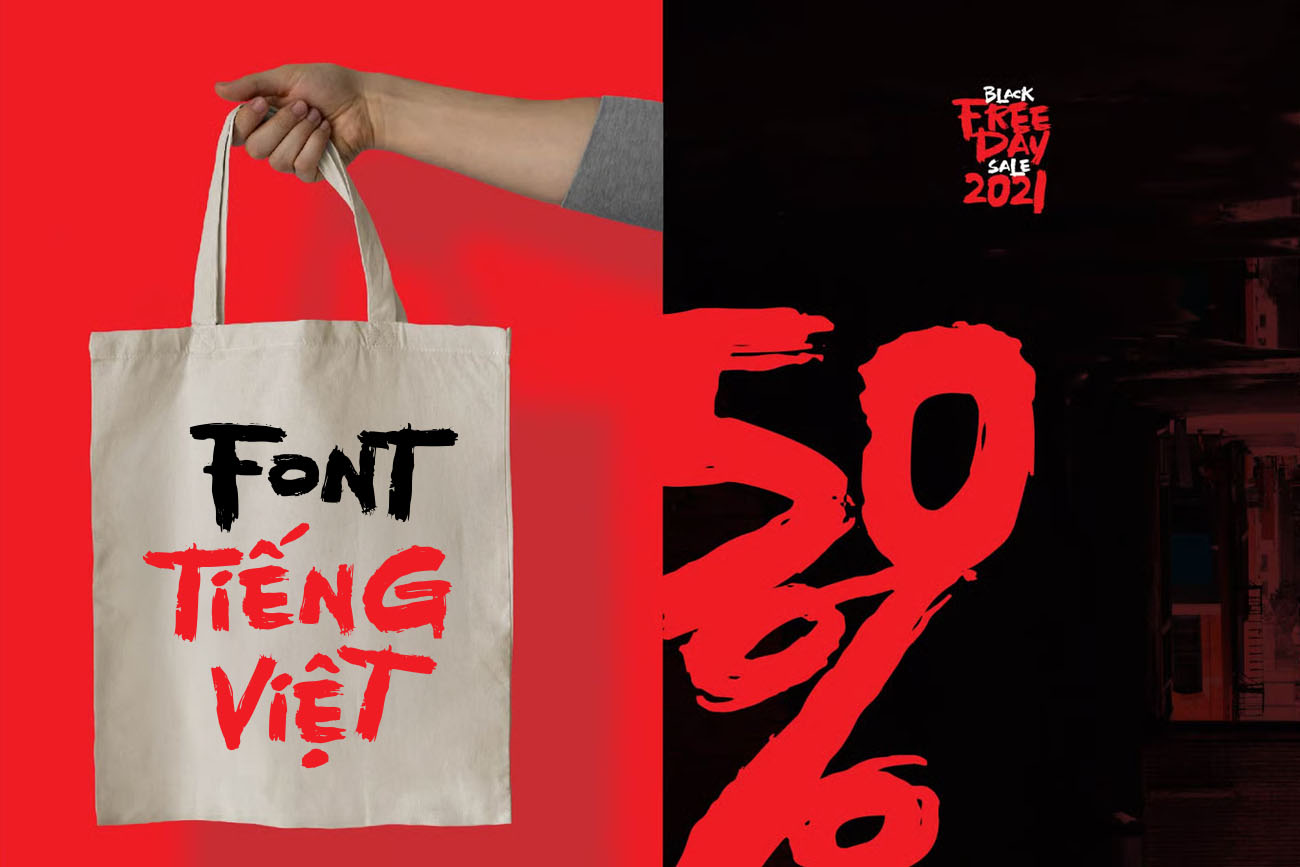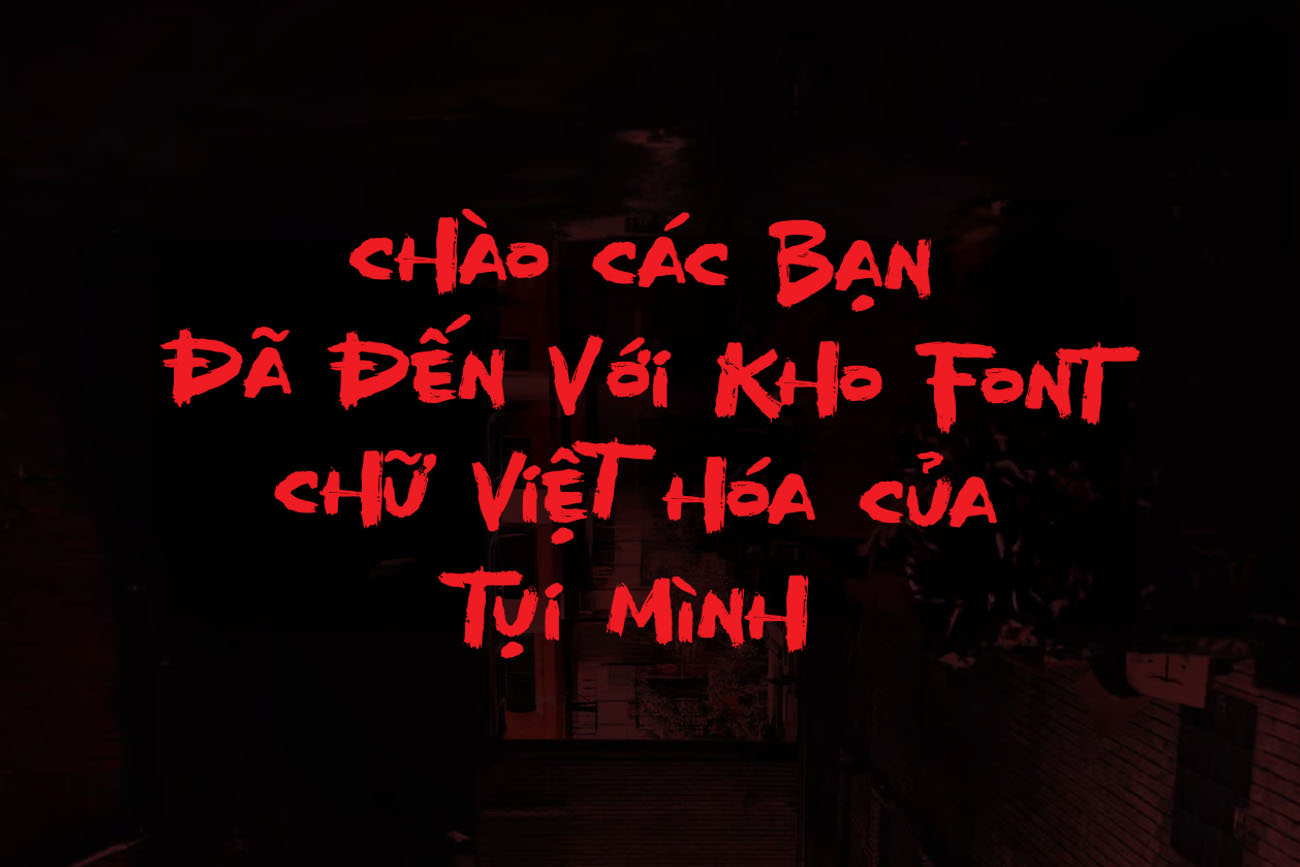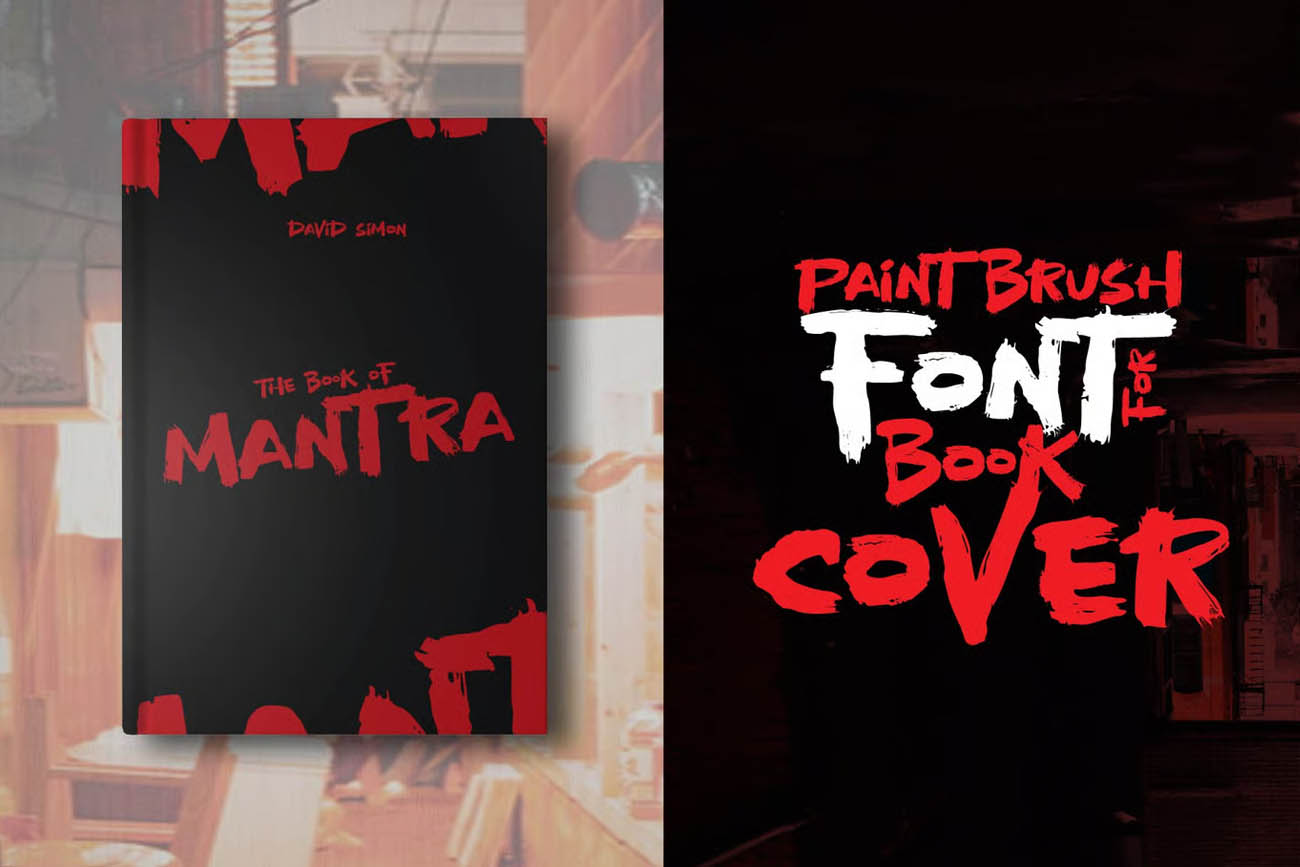
TH Dark Sincity - Sự Phá Cách Hoàn Hảo Cho Các Thiết Kế Mang Đậm Cá Tính
Tác giả Olex Studio
Trong thế giới thiết kế đồ họa, việc tìm kiếm một kiểu chữ thể hiện được sự mạnh mẽ, bụi bặm và gai góc luôn là một yếu tố quan trọng để tạo nên sự khác biệt. Bắt nguồn từ thiết kế gốc [Dark Sincity](https://elements.envato.com/fr/darksincity-display-font-PR9AQZN) của tác giả Olex Studio, phiên bản TH Dark Sincity đã chính thức ra mắt cộng đồng designer Việt. Đây là một luồng gió mới dành riêng cho những ai đang tìm kiếm sự phá cách độc đáo trong từng đường nét typography.
TH Dark Sincity: Sự Phá Cách Hoàn Hảo Cho Các Thiết Kế Mang Đậm Cá Tính
Đặc điểm nổi bật của TH Dark Sincity
Mang đậm hơi thở của văn hóa đường phố, thiết kế này là một font chữ hiphop tiêu biểu với các nét chữ dày dặn, sắc sảo và cấu trúc bất đối xứng đầy nghệ thuật. Không dừng lại ở đó, nhờ vào sự bí ẩn và những đường cắt xước góc cạnh trong từng ký tự, TH Dark Sincity còn được ứng dụng xuất sắc như một font chữ kinh dị trong các poster phim ảnh, bìa sách Halloween hay các ấn phẩm mang phong cách dark aesthetic. Sự đa năng này giúp các nhà thiết kế dễ dàng truyền tải những thông điệp thị giác tột độ và đầy ám ảnh.
Tại sao designer nên chọn phiên bản Việt hóa này?
Trước đây, việc sử dụng các phông chữ nước ngoài có thiết kế đặc thù thường gây khó khăn cho designer Việt vì lỗi hiển thị dấu. Tuy nhiên, với TH Dark Sincity, đây là một font chữ Việt hóa hoàn chỉnh. Các dấu câu được tinh chỉnh tỉ mỉ, đảm bảo tỷ lệ hài hòa tuyệt đối với bộ chữ gốc của Olex Studio. Điều này giúp bạn tiết kiệm tối đa thời gian kerning (chỉnh khoảng cách chữ) và vẽ lại dấu, mang đến trải nghiệm thiết kế mượt mà, chuyên nghiệp.
Đôi nét về đơn vị thực hiện TH Team
Quá trình chuyển ngữ và tối ưu hóa phông chữ này được thực hiện bởi TH Team – một đơn vị chuyên mang đến những giải pháp typography chất lượng cao cho người Việt. Bằng sự am hiểu sâu sắc về cấu trúc chữ cái, TH Team đã giữ nguyên được tinh thần nguyên bản của Dark Sincity trong khi vẫn đáp ứng hoàn hảo các quy tắc đánh vần phức tạp của tiếng Việt.
Lời kết
Nếu bạn đang ấp ủ một dự án thiết kế mang tính nổi loạn, underground hoặc cần một chút rùng rợn bí ẩn, TH Dark Sincity chắc chắn là mảnh ghép không thể thiếu trong thư viện tài nguyên của bạn. Hãy trải nghiệm ngay phiên bản tuyệt vời này để thổi bùng sự sáng tạo trong các tác phẩm đồ họa sắp tới!